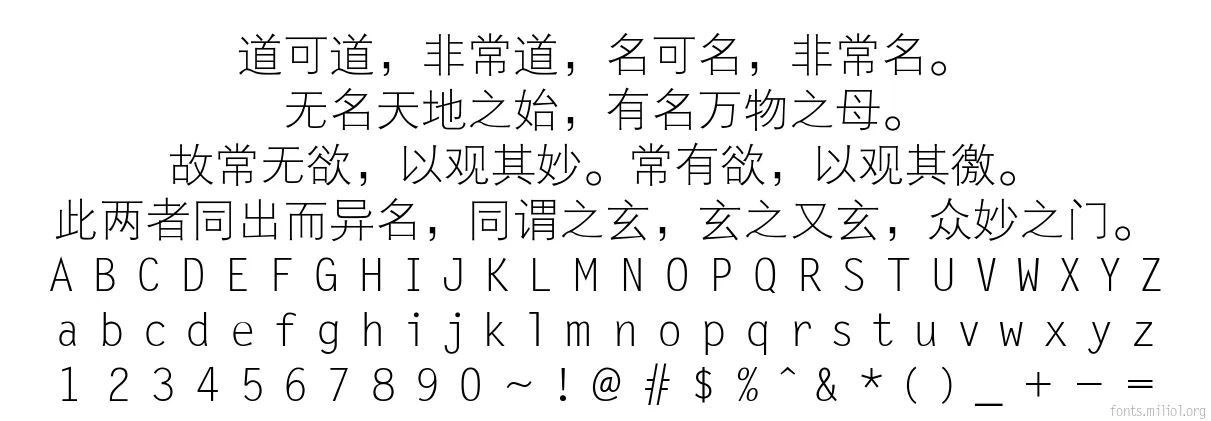
《方正细等线简体:简约之美与现代设计的完美融合》
方正细等线简体(FZXiDengXian-Z06S)是一款极具现代感的无衬线字体,以其纤细均匀的笔画和简洁利落的风格著称。作为方正字库的经典作品,它延续了等线体的几何特征,笔画粗细一致,结构清晰,尤其适合标题、广告、品牌标识等需要突出视觉张力的场景。其标准化的设计(GB1-0编码)确保了中文字符的规范性与兼容性,同时支持多平台应用。
这款字体在设计中能有效传递科技感与时尚气息,无论是数字界面还是印刷品,都能提升整体排版的高级感。其轻量化的线条既不会喧宾夺主,又能增强内容的可读性,是设计师青睐的实用字体之一。